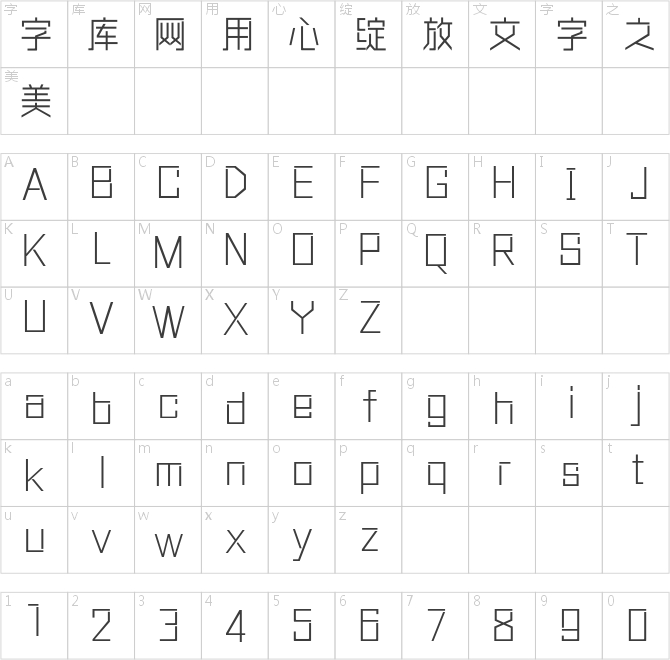
字體名稱: 三極新雅細黑簡
三極新雅細黑簡體
三極新雅細黑簡體介紹
三極新雅細黑簡體字體SJxinyaxihei-Regular字庫是一款讓人賞心悅目、百看不厭的中文字體,適合各類廣告和產(chǎn)品包裝設(shè)計應(yīng)用,字體大小1.58MB,格式為ttf字體,上傳用戶是三極字庫,作者/版權(quán)方為三極字庫